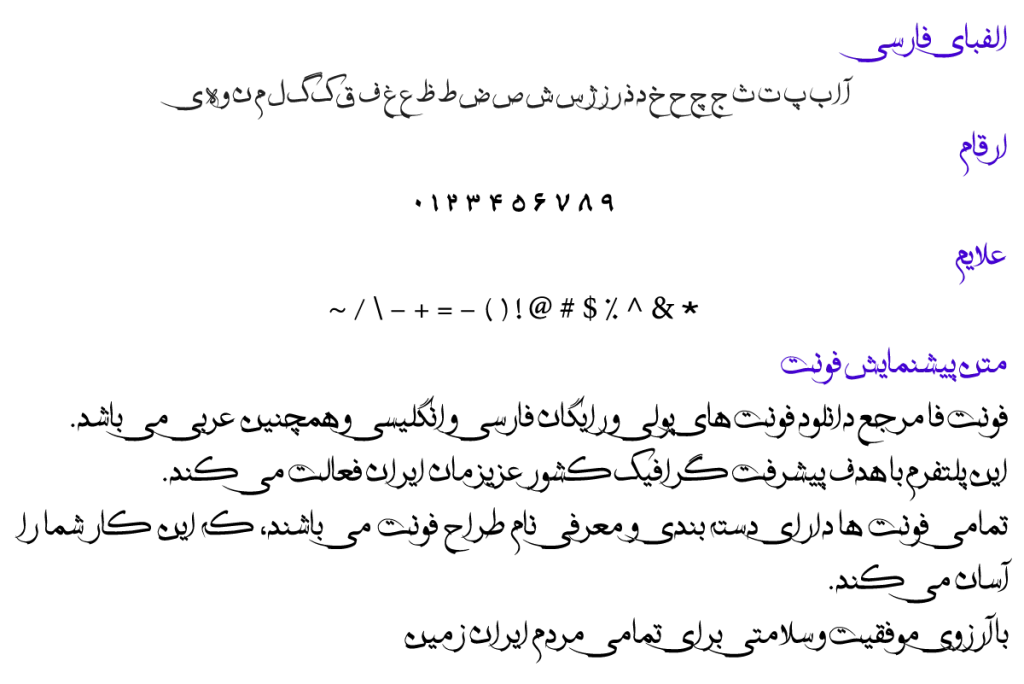
فونت فارسی خط خطی – Persian khat khati
طراح فونت: امیر حسین صدقی نوع فونت: فونت فانتزی
پیشنمایش فونت خط خطی
توضیحات و معرفی فونت خط خطی
فونت فارسی خط خطی ( Persian khat khati ) از مجموعه فونت های سری پرشین می باشد، و نیز نوع فونت فانتزی می باشد.
فونت خوشگل مربوط توسط امیر حسین صدقی طراحی و ساخته شده است.
در این فونت از خط های کرشمه، فونت ثلث و فونت نستعلیق شکسته و فونت ادوبی نسخ استفاده شده است.
در عکس زیر، شعر دل نشین وطن که با این تایپفیس طراحی شده، به نمایش درآمده است.